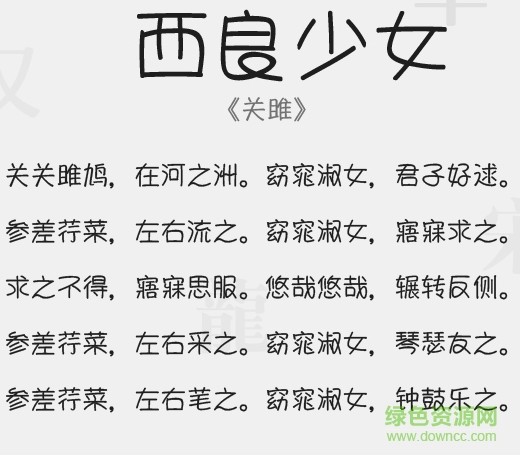
西良少女字體
西良少女字體是一款很生動活潑的藝術(shù)字體,有著如少女版姣好的姿態(tài),適合各種海報設(shè)計、藝術(shù)創(chuàng)作、排版設(shè)計等,快來綠色資源網(wǎng)下載看看吧!
西良少女字體字體介紹
字體簡介西良少女字體是一款用于平面設(shè)計方面的字體,支持中英文輸入,非常有古風感。